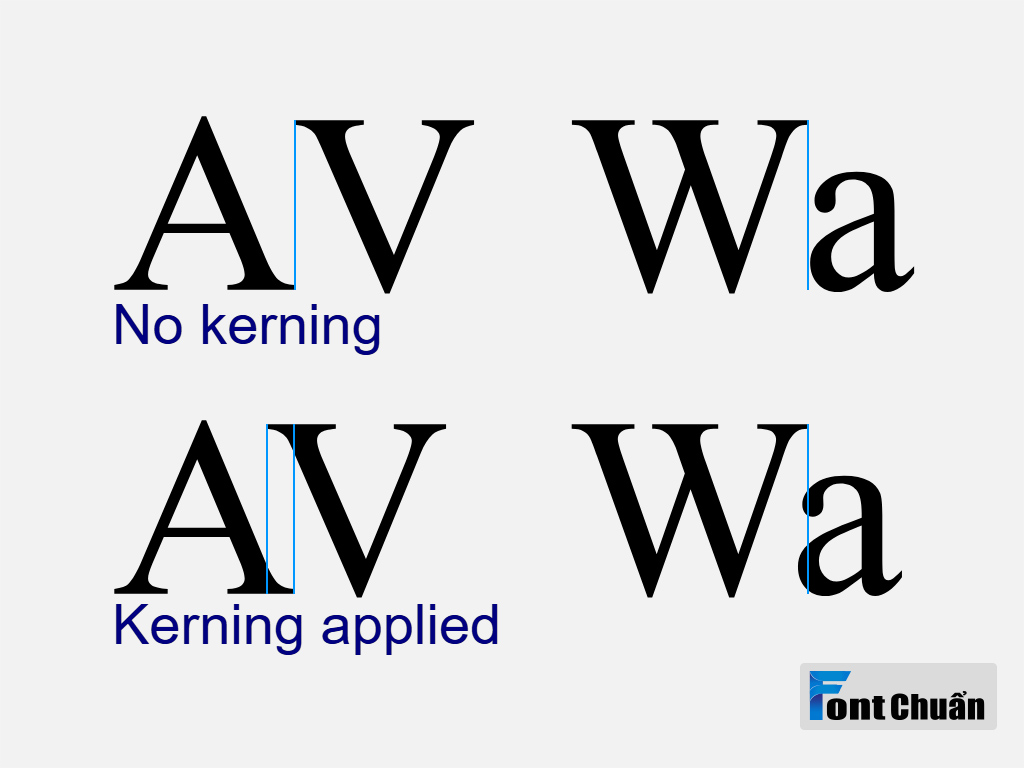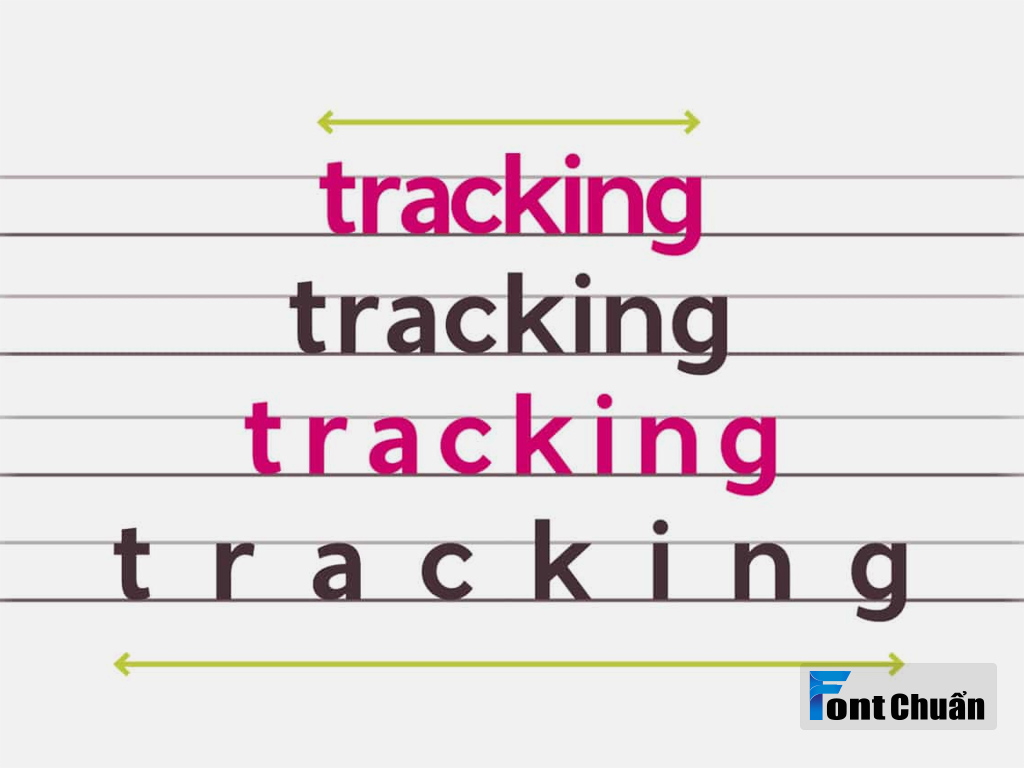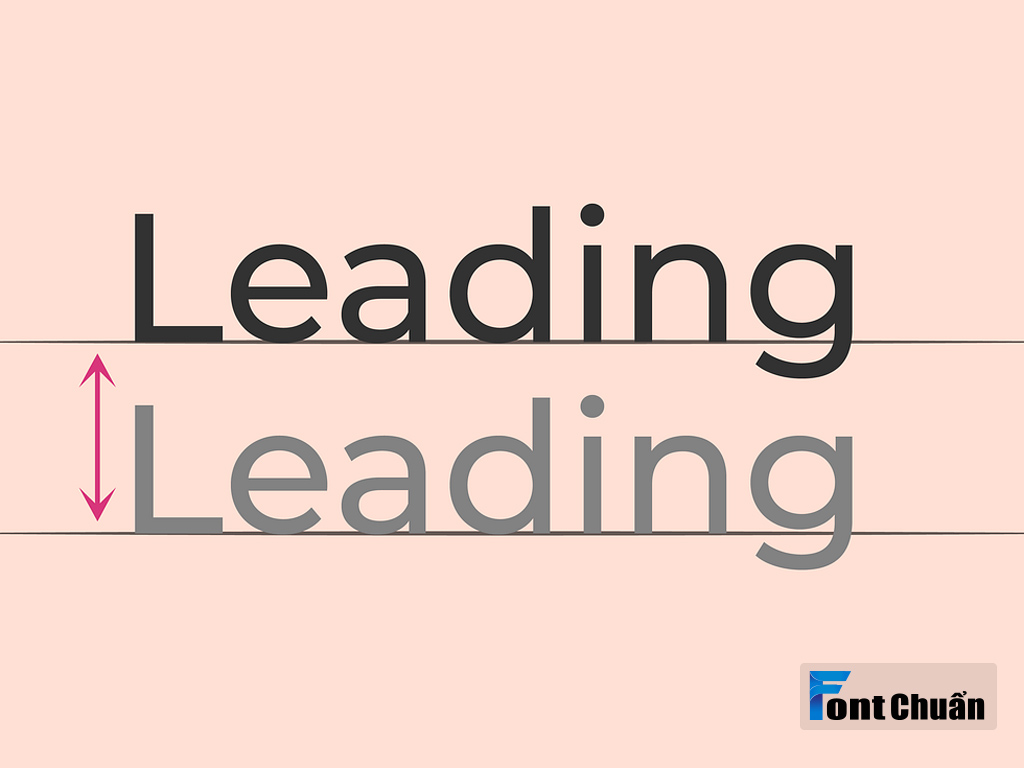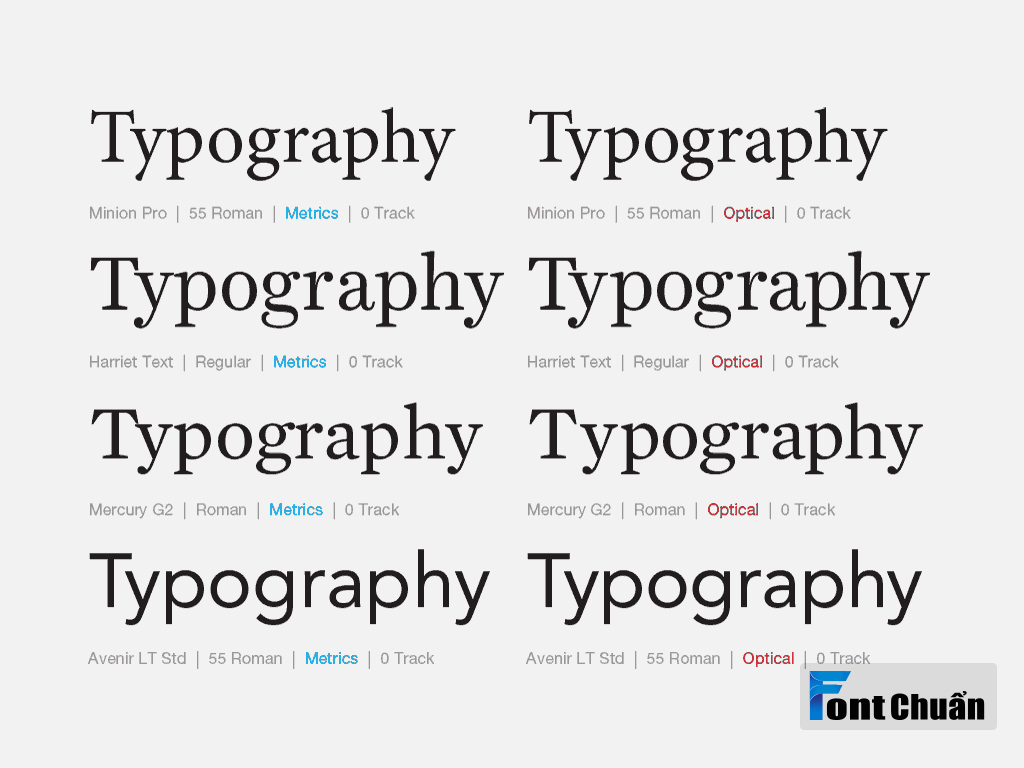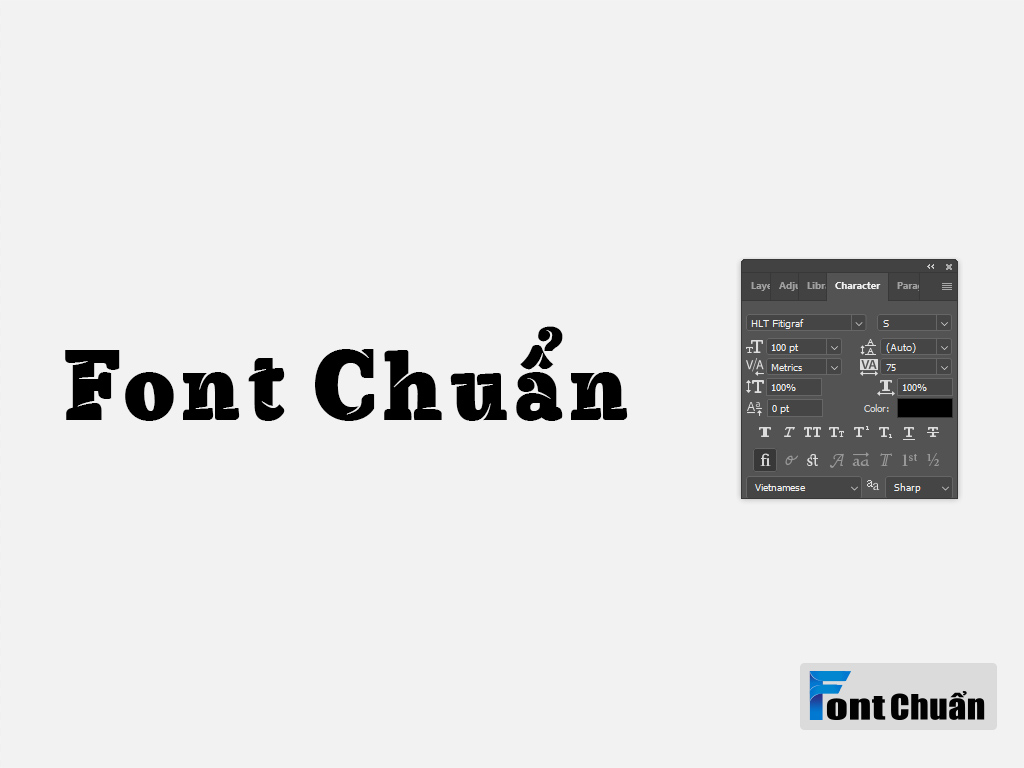
Kerning là gì? Phân biệt với Tracking và Leading
Trong thiết kế chữ, kerning đóng vai trò quan trọng giúp tối ưu khoảng cách giữa các ký tự, từ đó nâng cao tính thẩm mỹ và khả năng đọc của văn bản. Tuy nhiên, kerning thường bị nhầm lẫn với tracking và leading – hai khái niệm cũng liên quan đến khoảng cách trong typography. Vậy kerning là gì, khác gì với tracking và leading? Bài viết dưới đây của Font Chuẩn sẽ giúp bạn phân biệt rõ ràng từng thuật ngữ, đồng thời hiểu cách ứng dụng hiệu quả trong thiết kế đồ họa, in ấn và giao diện số (UI/UX).
Kerning là gì? Khái niệm cơ bản
Kerning là thao tác điều chỉnh khoảng cách giữa từng cặp ký tự nhằm tạo cân bằng thị giác và nâng cao khả năng đọc. Nếu không tinh chỉnh, các ký tự được xếp theo khoảng cách mặc định: cặp “A V”, “T o” có thể dính quá sát, trong khi “H H” hoặc “o o” lại thưa bất thường, khiến bố cục mất cân đối. Áp dụng kerning khắc phục hiện tượng này, giúp dòng chữ liền mạch, chuyên nghiệp và dễ tiếp thu hơn.
Kerning là gì? Khái niệm cơ bản
Khác với tracking (giãn đều toàn bộ chữ), kerning đòi hỏi chỉnh chính xác từng cặp, thể hiện sự tỉ mỉ của người thiết kế và tác động trực tiếp đến trải nghiệm đọc lẫn ấn tượng thẩm mỹ của văn bản.
Kerning, Tracking và Leading: Phân biệt các thuật ngữ quan trọng trong Typography
Trong lĩnh vực typography, bên cạnh kerning, còn có hai thuật ngữ quan trọng khác thường được nhắc đến là tracking và leading. Việc phân biệt rõ ràng giữa ba khái niệm này là nền tảng để hiểu và áp dụng hiệu quả các kỹ thuật sắp chữ.
Tracking (Letter-spacing) là gì?
• Tracking là việc điều chỉnh khoảng cách đồng đều giữa các ký tự trong toàn bộ một từ, câu hoặc đoạn văn. Khác với kerning (điều chỉnh cặp ký tự cụ thể), tracking tác động lên toàn bộ chuỗi ký tự cùng lúc.
• Tăng hoặc giảm tracking sẽ làm giãn cách hoặc thu hẹp toàn bộ chữ: khi tăng tracking, khoảng cách chữ rộng hơn giúp dòng chữ thoáng và dễ đọc hơn; khi giảm tracking, các chữ sát lại tạo cảm giác chặt chẽ hơn.
• Tracking thường được sử dụng để điều chỉnh bố cục văn bản: ví dụ căn chỉnh một dòng text để vừa một không gian thiết kế, hoặc xử lý trường hợp một từ bị rớt xuống dòng (widow/orphan) bằng cách nới hoặc siết khoảng cách chữ. Lưu ý không lạm dụng tracking – quá thưa hoặc quá dày đều có thể giảm tính dễ đọc của văn bản.
Tracking (Letter-spacing) là gì?
Leading (Line-height) là gì?
• Leading đề cập đến khoảng cách giữa các dòng chữ theo chiều dọc (còn gọi là giãn dòng). Đây là khoảng trống từ baseline (đường cơ sở) của dòng văn bản này đến baseline của dòng kế tiếp.
• Leading quyết định các dòng văn bản cách nhau bao xa: Leading phù hợp sẽ tạo khoảng trống thoải mái giữa các dòng, giúp đoạn văn dễ đọc và bố cục rõ ràng. Ngược lại, leading quá nhỏ làm các dòng chữ dính sát, gây rối mắt; leading quá lớn làm các dòng rời rạc, mất liên kết thị giác.
• Thông thường, leading được đặt khoảng 120% kích thước chữ để đảm bảo độ đọc tối ưu (ví dụ: chữ 10pt thì leading khoảng 12pt). Tuy nhiên, tùy thiết kế (ví dụ poster, văn bản sách báo), người thiết kế sẽ điều chỉnh line-height cho phù hợp nhằm đạt hiệu quả thẩm mỹ và đọc hiểu tốt nhất.
Leading (Line-height) là gì?
So sánh sự khác nhau giữa Kerning, Tracking và Leading
• Phạm vi tác động: Kerning chỉ điều chỉnh khoảng cách của một cặp ký tự cụ thể; Tracking điều chỉnh khoảng cách toàn bộ các ký tự trong một đoạn văn bản; còn Leading điều chỉnh khoảng cách giữa các dòng văn bản.
• Chiều không gian: Kerning và Tracking tác động trên trục ngang (khoảng cách chữ cái trong dòng), trong khi Leading tác động trên trục dọc (khoảng cách dòng trên dưới).
• Mục đích sử dụng: Kerning dùng để tinh chỉnh cặp chữ cho đẹp mắt (thường hữu ích khi thiết kế logo, tiêu đề); Tracking dùng để căn chỉnh tổng thể độ rộng của khối chữ (điều chỉnh độ đặc/thưa của đoạn văn hoặc dòng chữ để phù hợp bố cục); Leading dùng để điều tiết nhịp độ dòng trong đoạn văn, đảm bảo văn bản dễ đọc và hài hòa trên trang.
• Tương quan với font chữ: Cả kerning, tracking và leading đều phụ thuộc vào đặc điểm typeface/font sử dụng. Mỗi font thiết kế sẵn một khoảng cách mặc định giữa các chữ và dòng; nhà thiết kế cần hiểu rõ để điều chỉnh phù hợp: ví dụ, font chữ kiểu đẹp có đường nét trang trí có thể cần kerning kỹ hơn, hay văn bản dài (như sách, báo) thường dùng leading mặc định lớn để dễ đọc.
Để làm rõ hơn sự khác biệt giữa ba thuật ngữ này, chúng ta có thể xem xét bảng so sánh sau:
Thuật ngữ Đối tượng điều chỉnh Phạm vi tác động Mục đích chính
Kerning Khoảng cách giữa hai ký tự cụ thể (Space between two specific characters) Từng cặp ký tự (Individual character pairs) Cải thiện sự hài hòa thị giác giữa các ký tự (Improve visual harmony between characters)
Tracking Khoảng cách giữa tất cả các ký tự (Space between all characters) Toàn bộ từ hoặc đoạn văn (Entire word or paragraph) Điều chỉnh độ dài dòng, tạo hiệu ứng (Adjust line length, create effects)